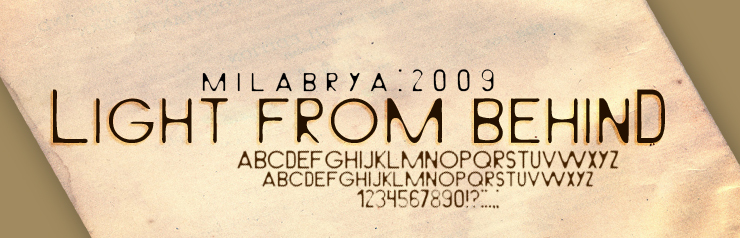
Light From Behind, entworfen von Yuliyan Ilev, ist eine kostenlose, handgezeichnete Sans-Serif-Display-Schrift mit schmalen, abgerundeten Strichen und sanft unregelmäßigen Formen. Der Schriftzug wirkt offen, entspannt und unverfälscht handgemacht.
Einfache Strichzeichnungen greifen ihre weichen Konturen auf, wodurch sie sich gut für Buchcover, Café-Verpackungen und Kunstplakate eignet. Ihr informeller Zeichenstil passt zudem zu Indie-Musik-Grafiken und Materialien für Gemeinschaftsveranstaltungen, bei denen die Buchstaben wie ein Teil des Kunstwerks wirken.